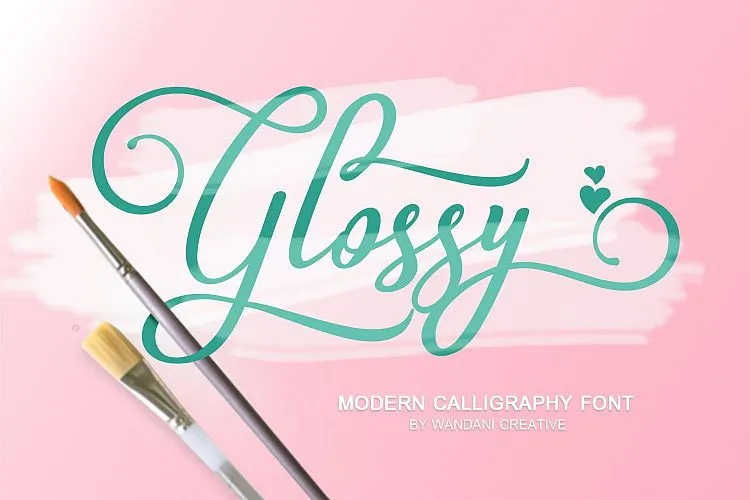
A Glossy Script Font é uma fonte script moderna que traz a elegância do estilo de arte à sua próxima criação. Introduzida pela M.0Type, essa fonte é perfeita para quem busca um toque sofisticado e charmoso em seus projetos digitais. Seu design suave e arredondado permite criar designs de caligrafia capturando o brilho e a elegância que as pessoas adoram nos materiais impressos. Com várias letras individuais e ligaduras, é uma fonte versátil que pode transformar simples ideias em criações única. Ideal para identidades corporativas, embalagens, logos, arquivos de casamento ou qualquer projeto em que você deseje adicionar um toque de elegância moderna. Quebre o código e experimente esta fonte; ela é certamente uma maneira criativa de dar vida a seu design!